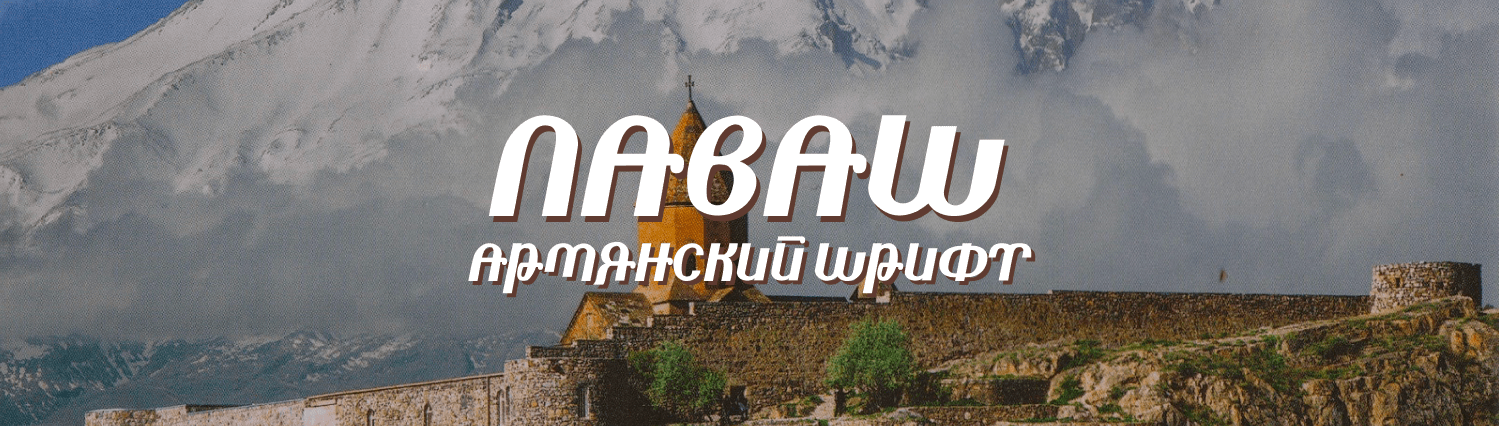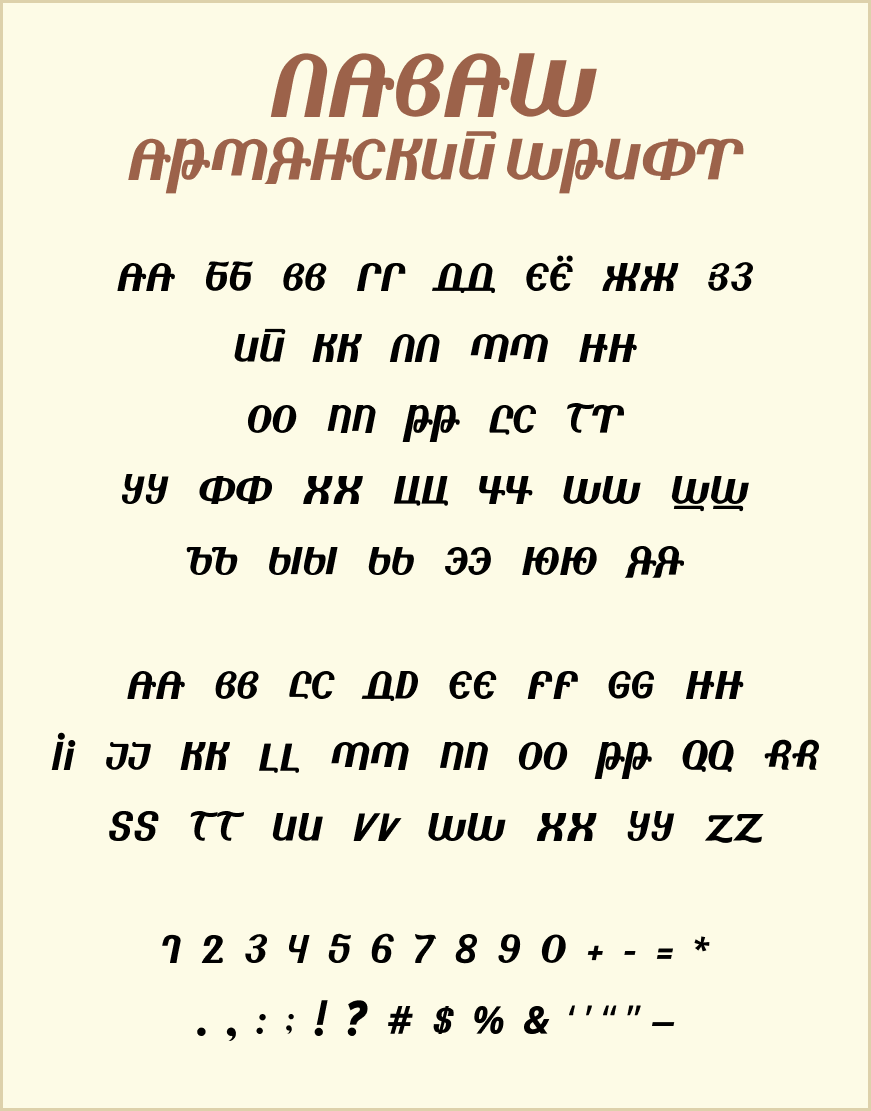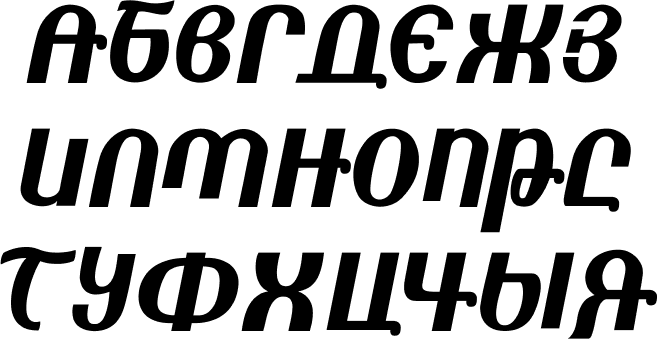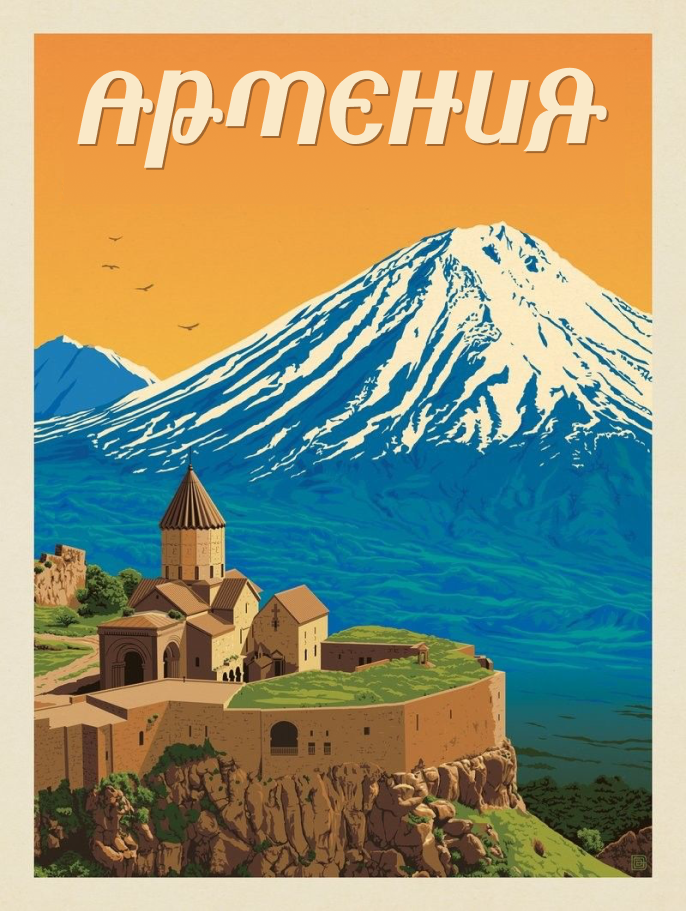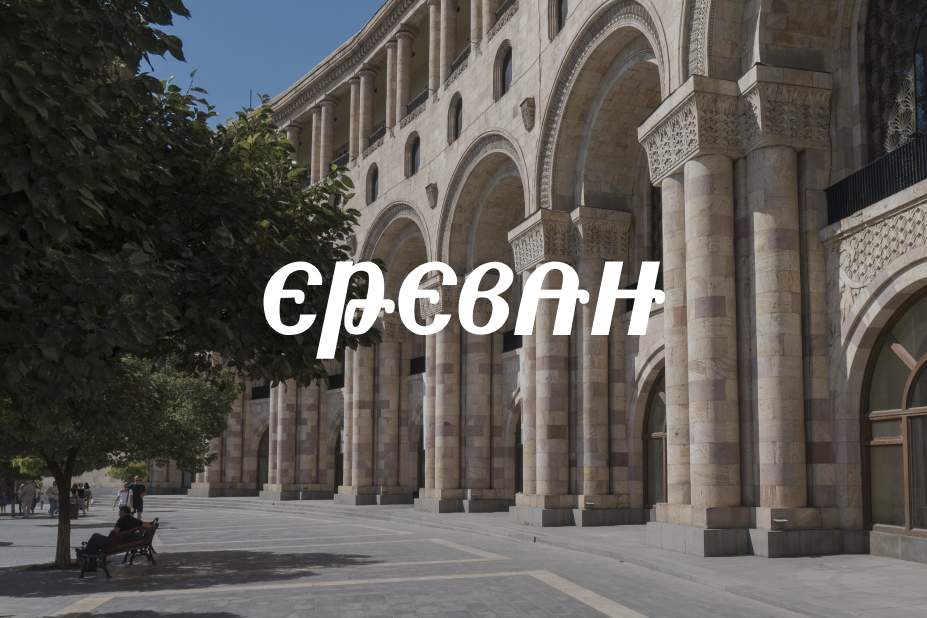
Шрифт в армянском стиле Лаваш
Лаваш — кириллический шрифт в армянском стиле. Шрифт включает буквы латинского и кириллического алфавита, цифры, несколько основных знаков препинания и математических символов.
Шрифт Лаваш создан по образцу леттеринга, случайно найденному по запросу “шрифт в армянском стиле”. Автору неизвестно других стилизаций кириллицы под армянский алфавит. Похоже, что Лаваш — единственный шрифт в своем роде.
Большинство букв нарисованы по образцу. Некоторые буквы несильно изменены в целях лучшей адаптации для цифрового шрифта.
Армянские буквы отличаются скругленными формами и длинными основными штрихами. Человеку, не знающему армянский алфавит, буквы кажутся набором труб, согнутых в разных формах.
Благодаря такой простой форме и родству с кириллицей шрифт в армянском стиле изготовить достаточно легко. В отличие, к примеру, от арабской вязи, где каждую букву приходится отрисовывать практически с нуля, в армянском алфавите формы часто повторяются. Нет в шрифте и лигатур: он слишком простой для них, как, впрочем, и для кернинговых пар.
Зато некоторые буквы выполнены в двух вариантах: основном и упрощенном, из-за специфической формы оригинала.
Шрифт Лаваш передает колорит армянских букв. Вытянутые, скругленные формы шрифта вызывают однозначную ассоциацию с Арменией.
Лаваш прекрасно подойдет для оформительских задач. Шрифт идеально ложится на советские постеры и винтажные открытки.